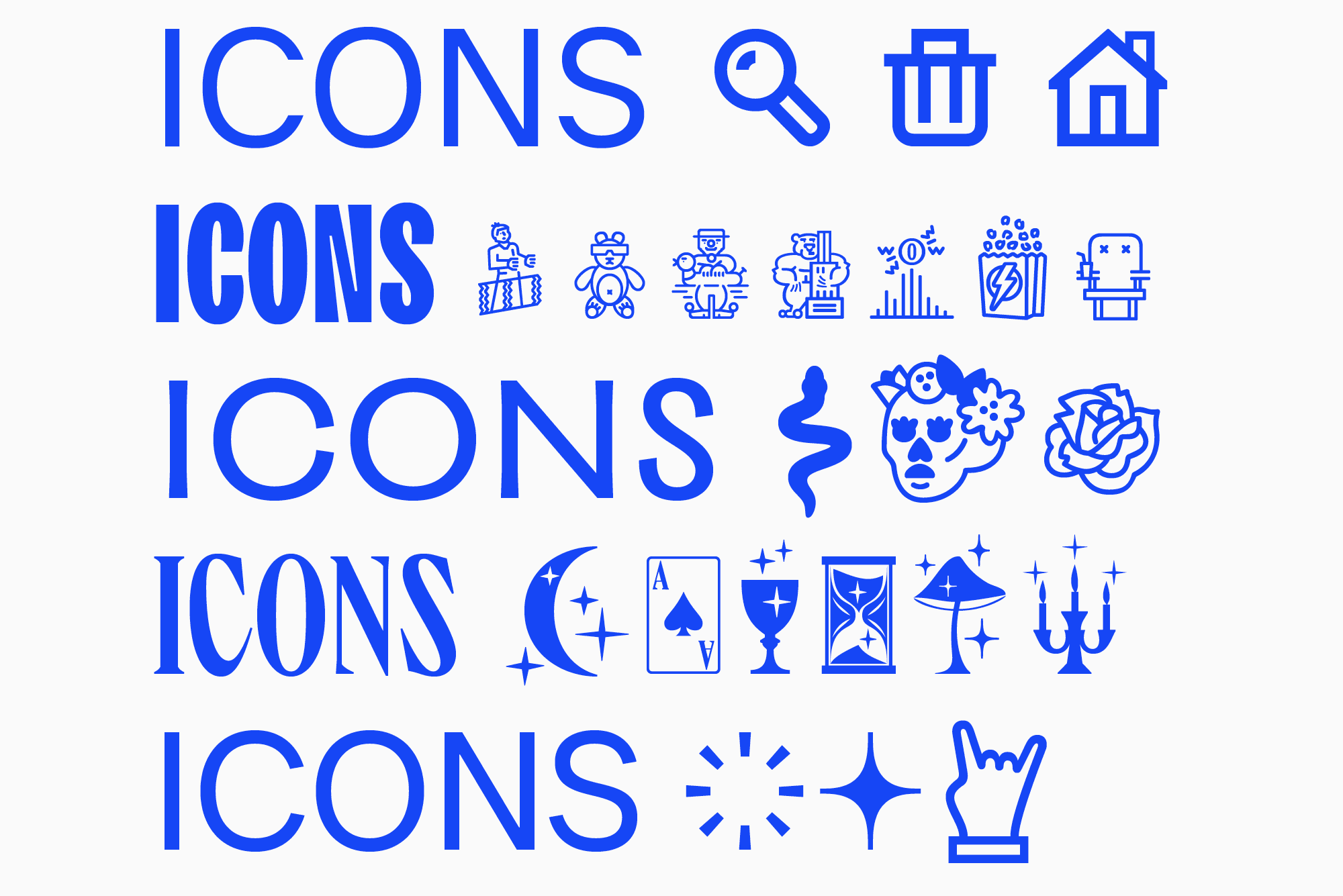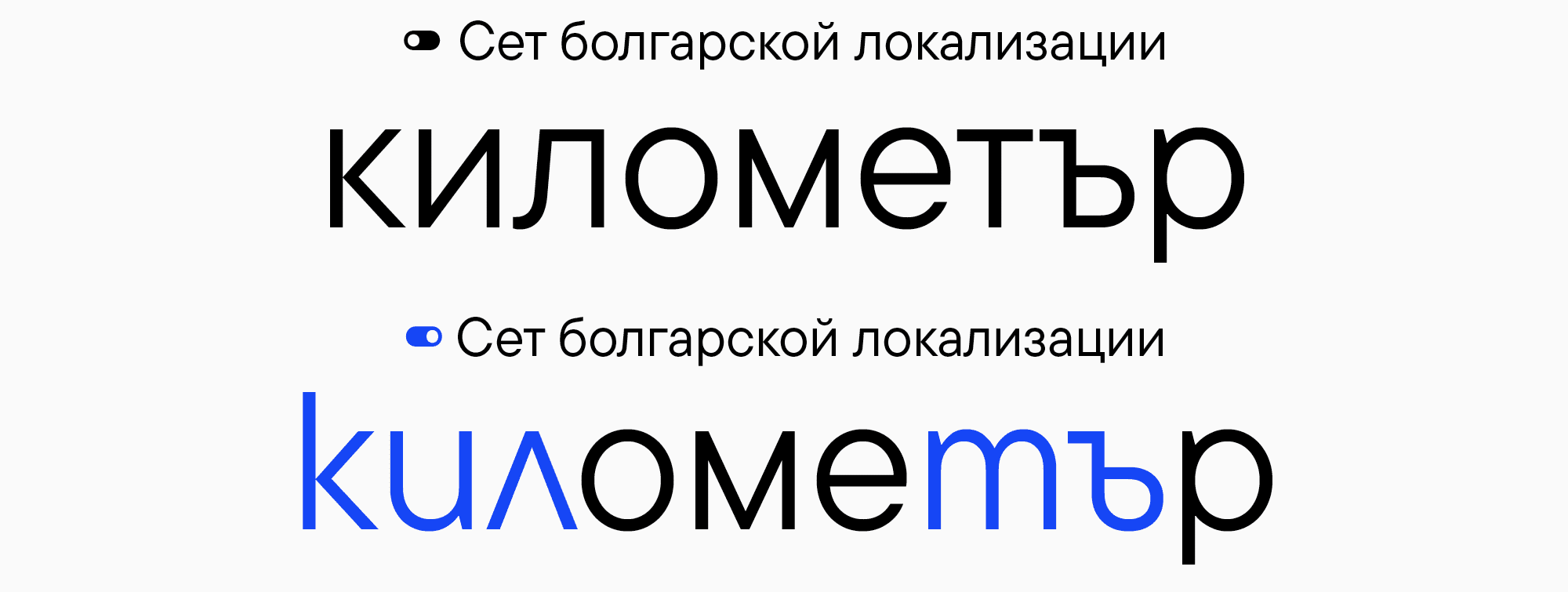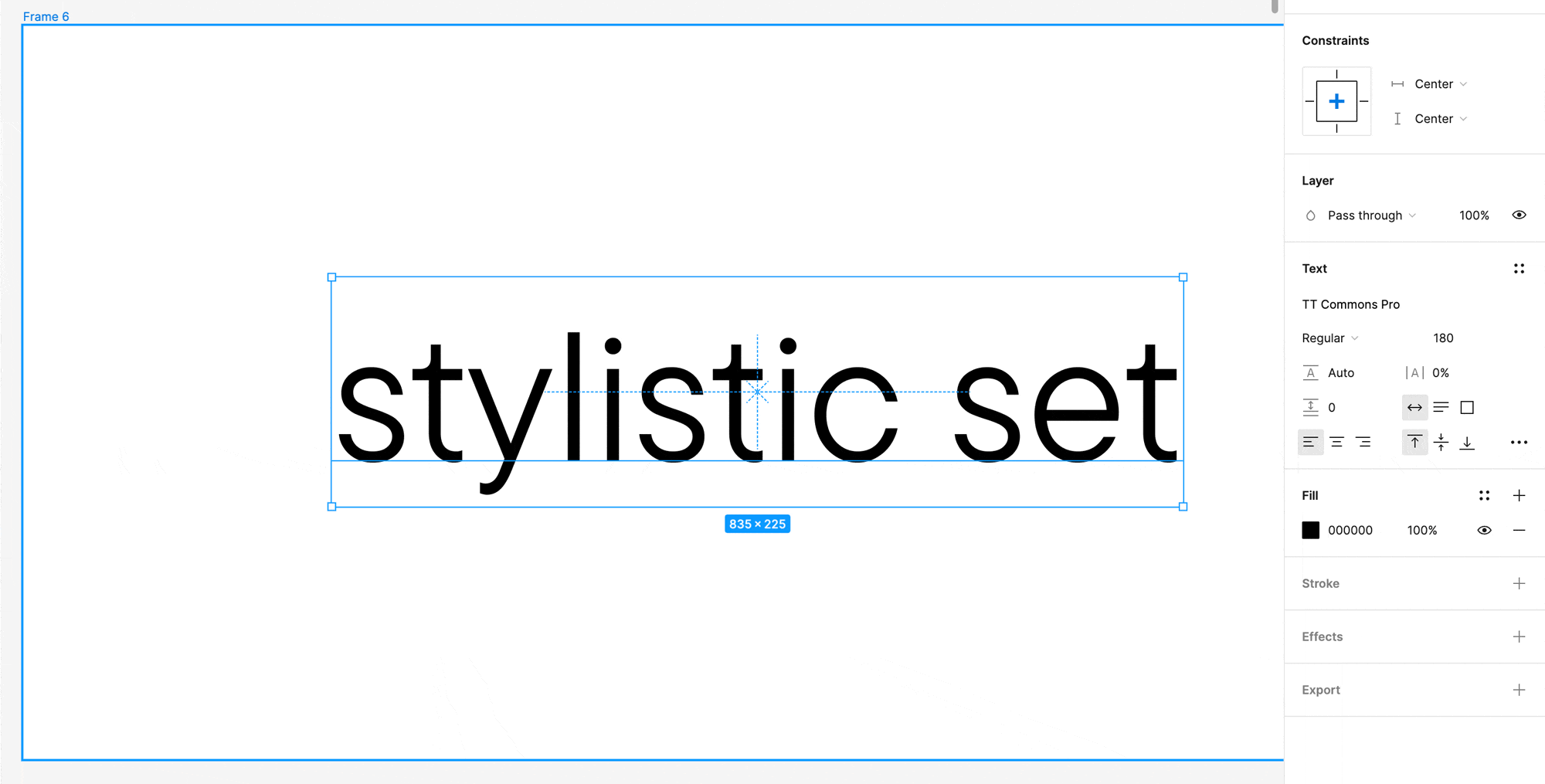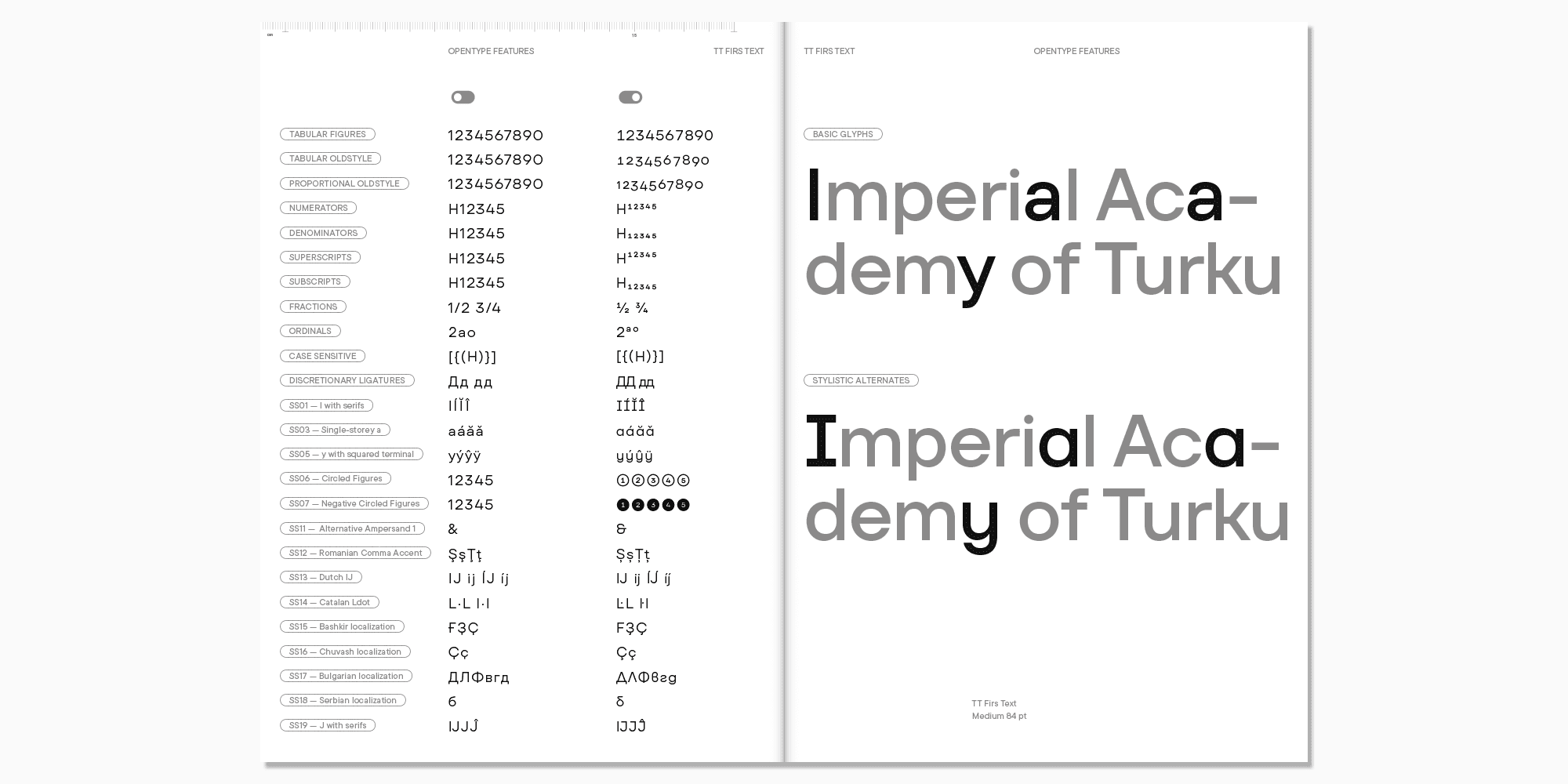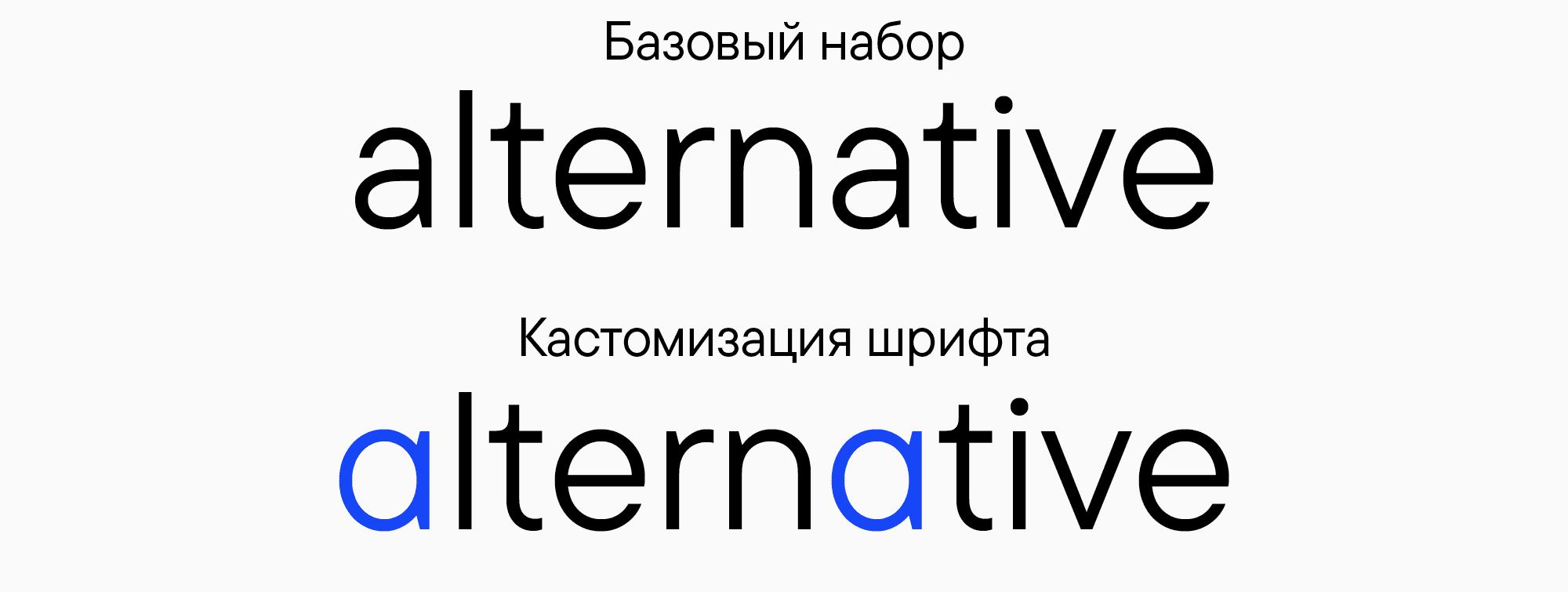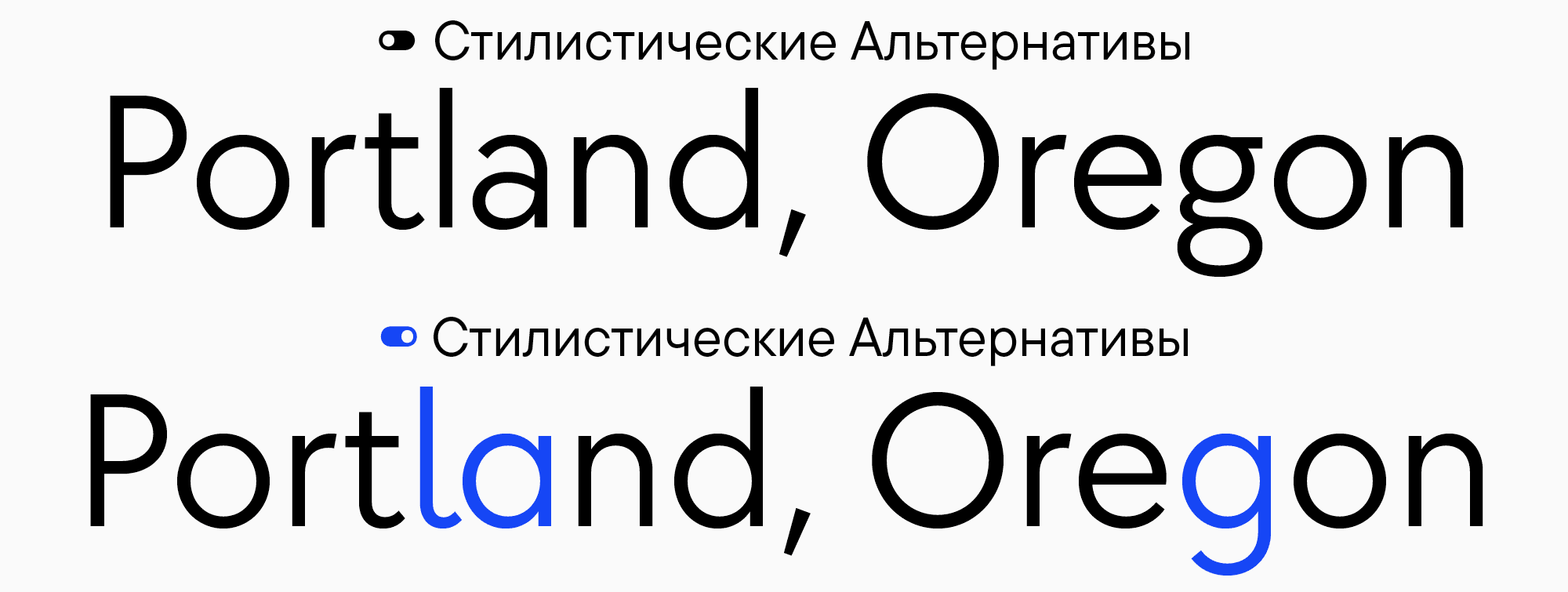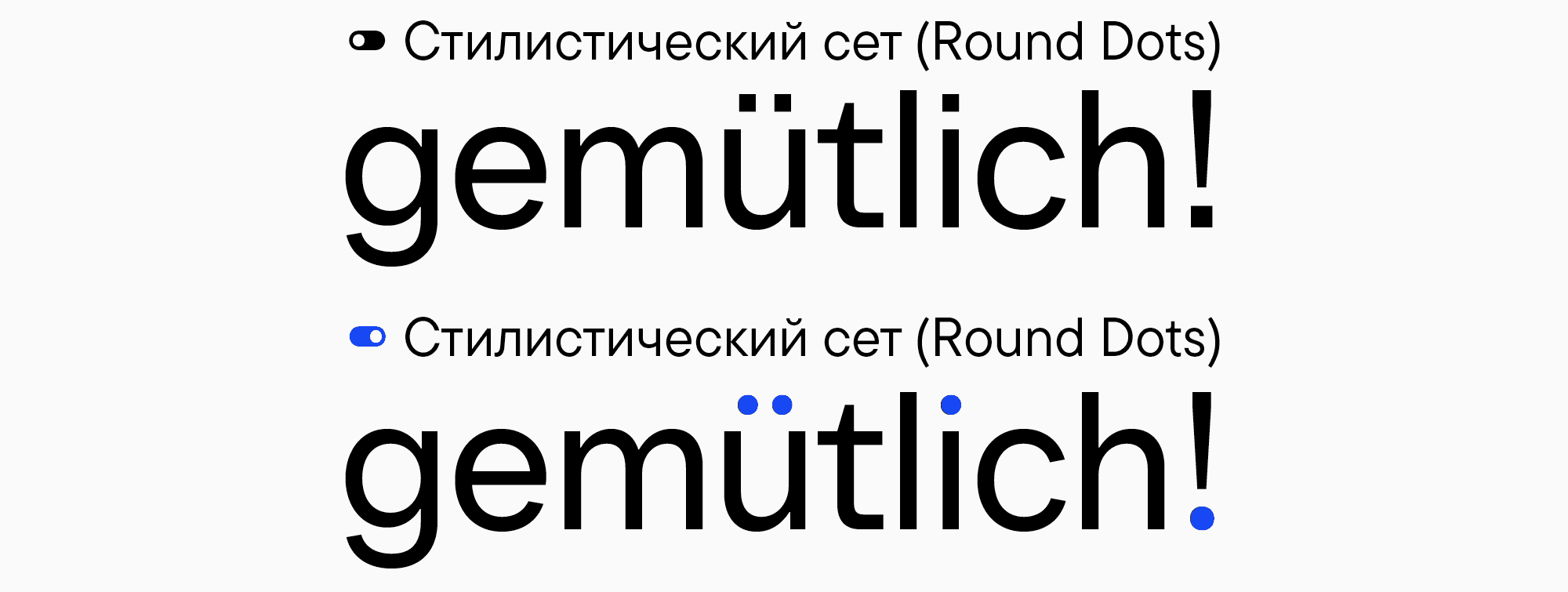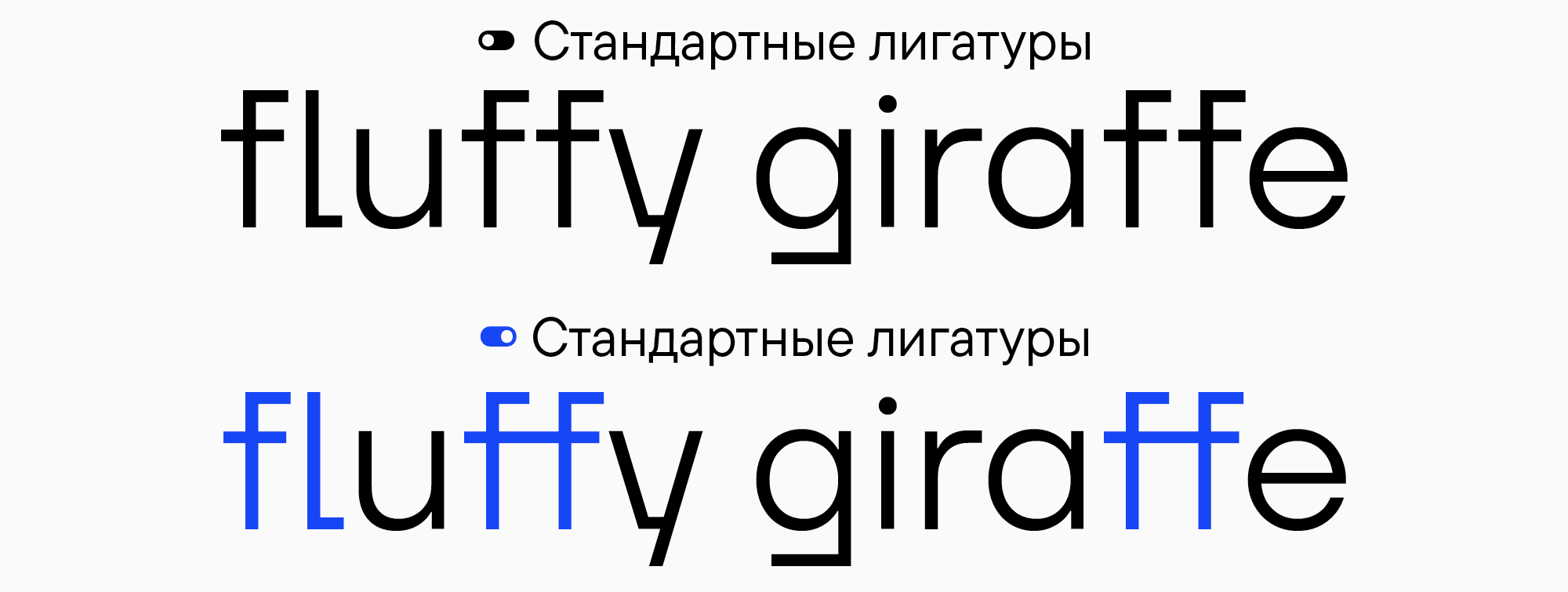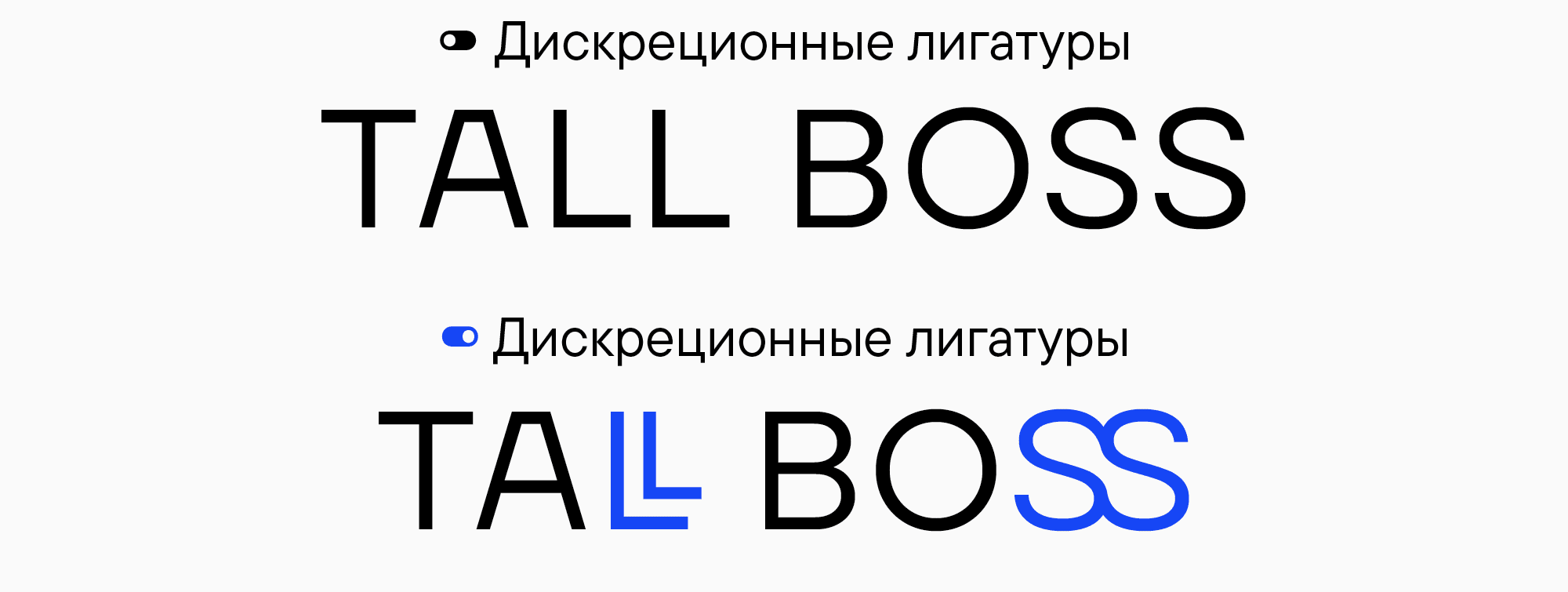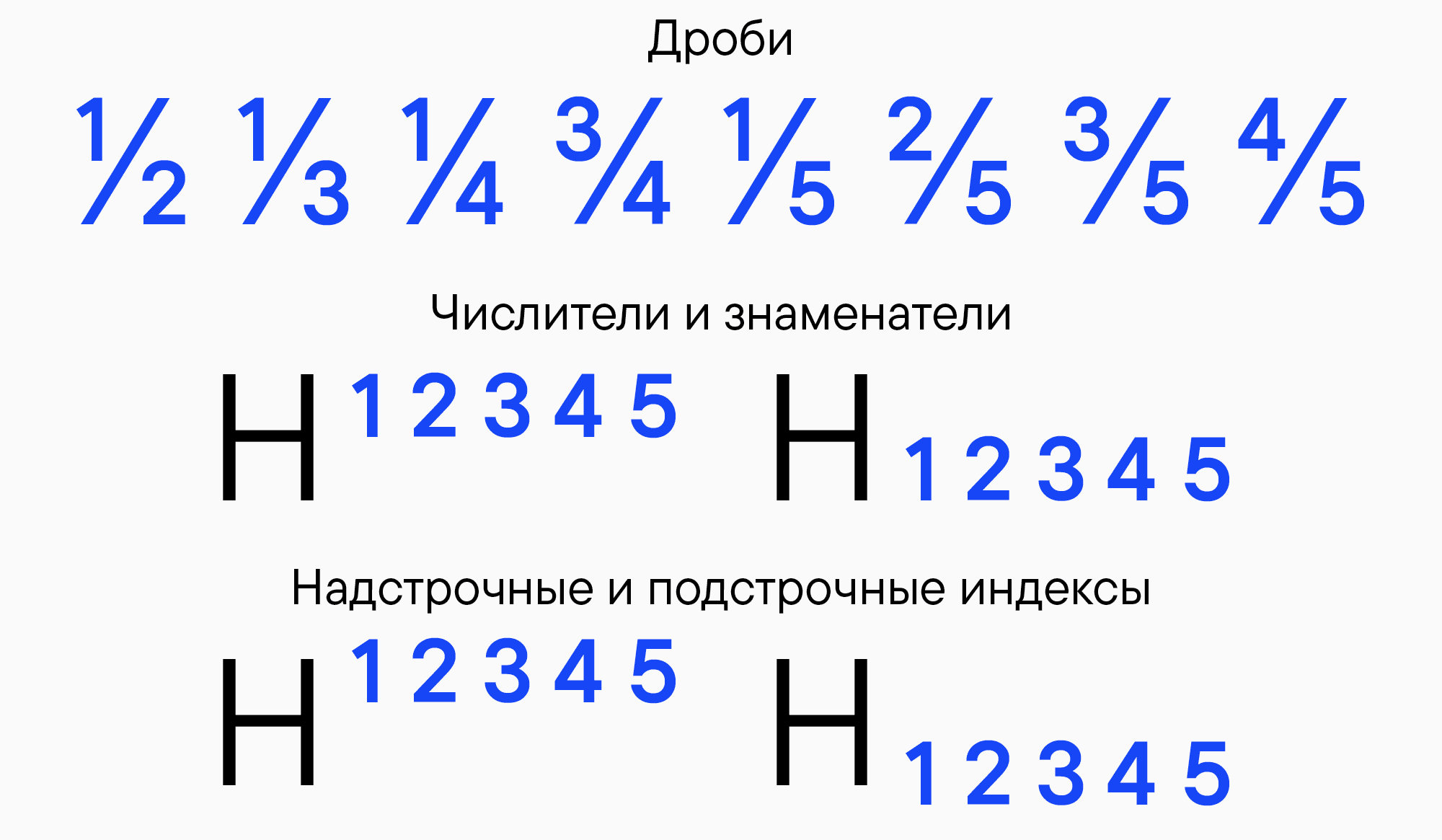
Функции OpenType: как ими пользоваться?
В шрифтах заложено очень много интересных возможностей. Однако многие дизайнеры либо вовсе не знают, что эти возможности существуют, либо не понимают, как ими пользоваться. Но на самом деле никто от вас ничего не скрывает: все эти инструменты очень легко найти. Главное — знать, что именно искать.
В этой статье мы расскажем, что такое функции OpenType (они же — OpenType фичи).
Что такое функции OpenType?
OpenType фичи (OpenType features) — это те самые «скрытые возможности» шрифта, инструменты, которые в него заложены. У них есть несколько задач, которые можно разделить на две группы: технические и художественные.
Технические OpenType свойства направлены на то, чтобы улучшить верстку. Разработчики шрифта чаще всего хотят, чтобы их шрифт хорошо работал и им было удобно пользоваться. Поэтому они делают все, чтобы дизайнеры с легкостью могли использовать весь функционал гарнитуры.
Художественные фичи — это стилистические сеты и альтернативы, которые позволяют дизайнеру самостоятельно подстроить внешний вид шрифта под проект, придать ему определенный характер и индивидуальность.
Что такое функции OpenType?
Удобство — отличительное свойство шрифтов, в которых заложены опентайп фичи. Шрифт OpenType по сравнению с форматом TrueType обладает бо́льшими возможностями, о которых мы и расскажем ниже.
Для чего используются OpenType фичи и какими они бывают?
Давайте разберемся, какие опентайп фичи существуют и как использовать каждую из функций.
Стилистические сеты
Часто в одной гарнитуре заложено несколько форм одних и тех же букв. Например, одночастная и двухчастная «а» — это альтернативные формы одного и того же знака. Их может быть очень много — все ограничивается лишь фантазией шрифтового дизайнера. Многие из этих альтернатив несут чисто графические, художественные функции. Но у некоторых есть и практическое свойство. Например, буква «l» (эль) с хвостиком очень часто необходима при навигационных задачах, чтобы не перепутать ее с прописной буквой «I» (ай), потому что они выглядят похоже.
Стилистические сеты
Часто некоторые альтернативные формы имеют схожие характерные особенности, поэтому их объединяют в группы, которые называются стилистическими сетами. Стилистический сет — это набор знаков с общей альтернативной формой. С помощью стилистических сетов можно менять характер шрифта: например, превратить нейтральный гротеск в мягкий, веселый и даже игривый. И все это — за счет изменения формы некоторых букв. Но речь не только об отдельных буквах: если мы, например, хотим поменять форму точек, у нас будут меняться все знаки, в конструкции которых есть точки — а таких знаков достаточно много.
Стилистические сеты
Все они чаще всего собираются в целый сет, чтобы не пришлось менять каждую букву отдельно, ведь это займет много времени — тем более, если это объемный текстовый документ или книга. Вы можете просто включить этот сет, и все знаки во всем текстовом блоке или документе поменяются. Это очень удобная функция.
Лигатуры
Лигатуры — это знаки, образованные путем соединения нескольких глифов. Лигатуры бывают стандартными и дискреционными. Стандартные лигатуры есть практически в каждом шрифте: например, fi, fl, ff, ffi, ffl, ft. Они несут практические функции.
Лигатуры
Дискреционные лигатуры отличаются от стандартных тем, что их назначение скорее декоративное, и это могут быть любые сочетания букв — все зависит от фантазии автора и специфики проекта. Любые знаки, которые дизайнер захотел соединить и увидел в этом практический и эстетический смысл, превращаются в дискреционные лигатуры. Среди них можно найти крайне необычные решения, которые могут очень интересно выглядеть в дизайн-проектах.
Лигатуры
Цифры
Специальные знаки, основанные на цифрах, также часто встречаются в шрифтах. Например, во многих шрифтах есть дроби. Существует огромное множество разных сочетаний. Еще есть разные варианты маленьких цифр, таких как надстрочные и подстрочные индексы, а также числители и знаменатели , из которых составляются дроби.
Цифры
Также во многих шрифтах есть табулярные цифры — это цифры, которые вписываются в одинаковую ширину площадок. Грубо говоря, это «моноширинные цифры». Их очень удобно использовать в случаях, когда важно, чтобы каждая цифра в следующей строке оказывалась ровно под цифрой из строки выше. Например, в таблицах.
Цифры
Еще одна интересная находка для дизайнеров — цифры в кружочках. Они бывают двух видов: в залитых и пустых кружочках. Обычно такие цифры находятся внутри стилистических сетов. Служат для декоративных целей.
Цифры
Кроме того, существуют старостильные цифры. Они отличаются по форме от привычных нам современных цифр. Их можно использовать, чтобы придать ощущение историчности вашему проекту. А в паре с ними можно использовать старостильные валюты — еще одну фичу, заложенную во многих шрифтах.
Цифры
Иконки